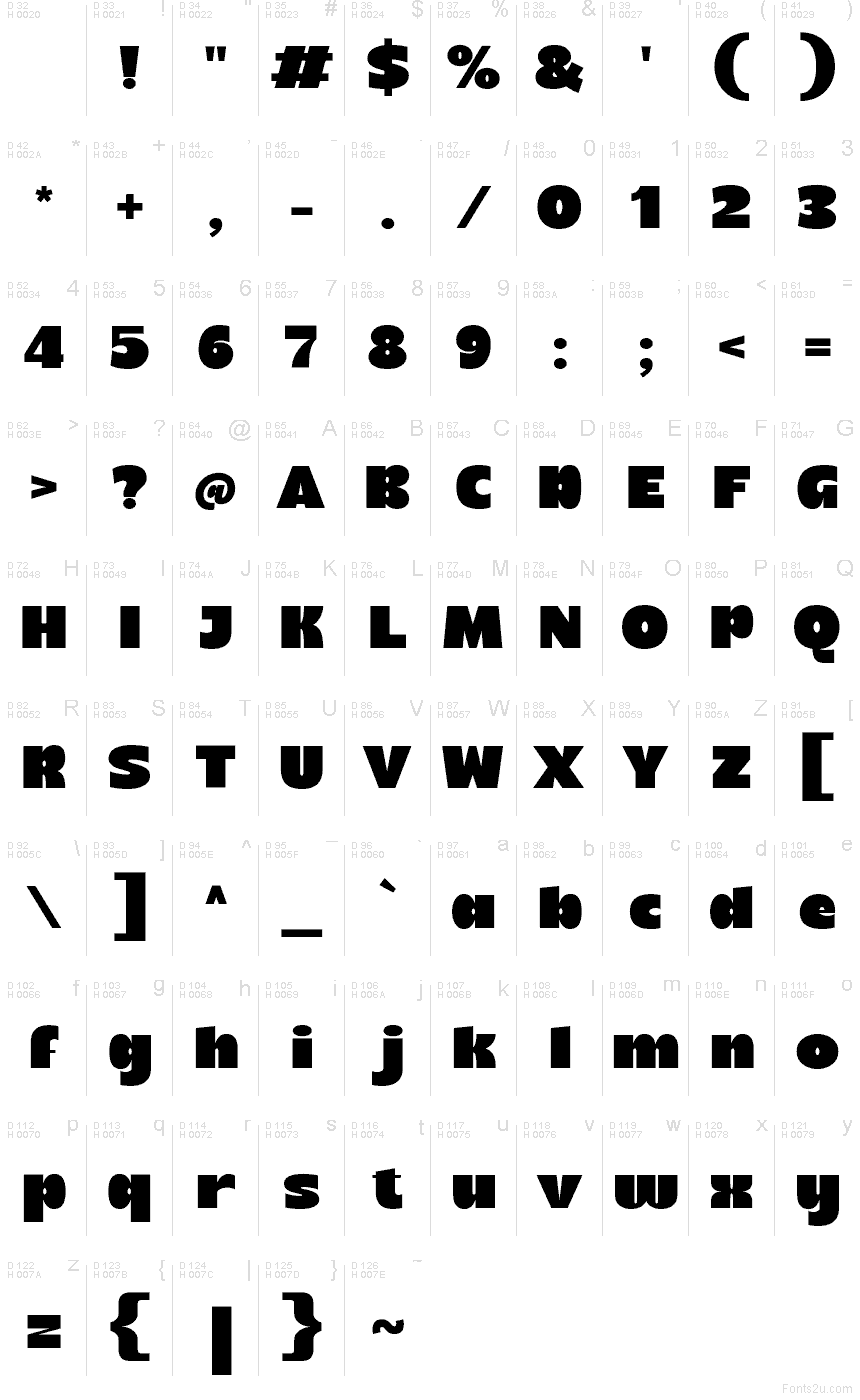
Il font Cloth Fate di Burhan Afif (HansCo Studio) si presenta come un blocco di inchiostro: extra-bold, arrotondato e audacemente massiccio, con contatori stretti e un ritmo leggermente compresso che ricorda il taglio di un tessuto pesante. È un carattere sans serif gratuito che si fa notare al primo sguardo, mantenendo intatta la sua forma su schermi, poster o packaging senza risultare confusionario.
Cloth Fate è perfetto per loghi streetwear, copertine di album, titoli d'impatto, sticker design, merchandising sportivo, confezioni di snack e pubblicità accattivanti sui social. Usalo in grande formato con un tracciamento generoso per far respirare le forme pesanti, e abbina questo font gratuito a un sans serif pulito e leggero per il testo principale.